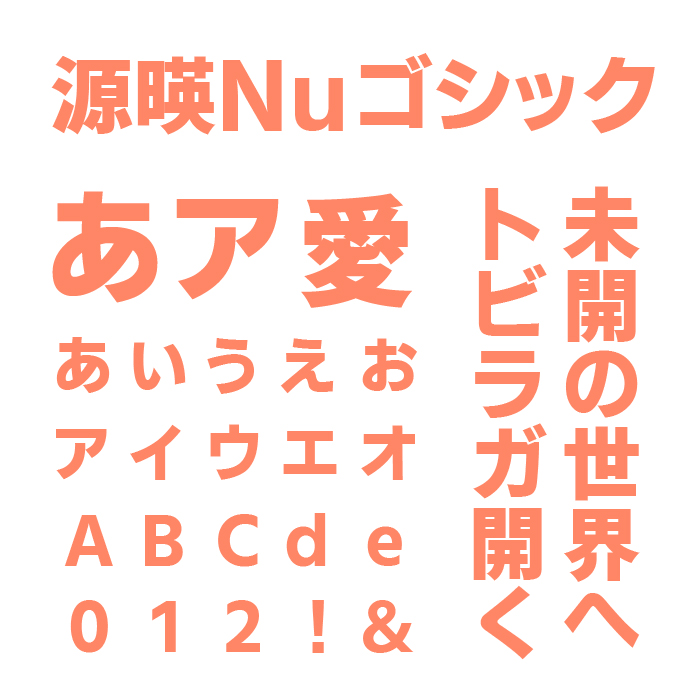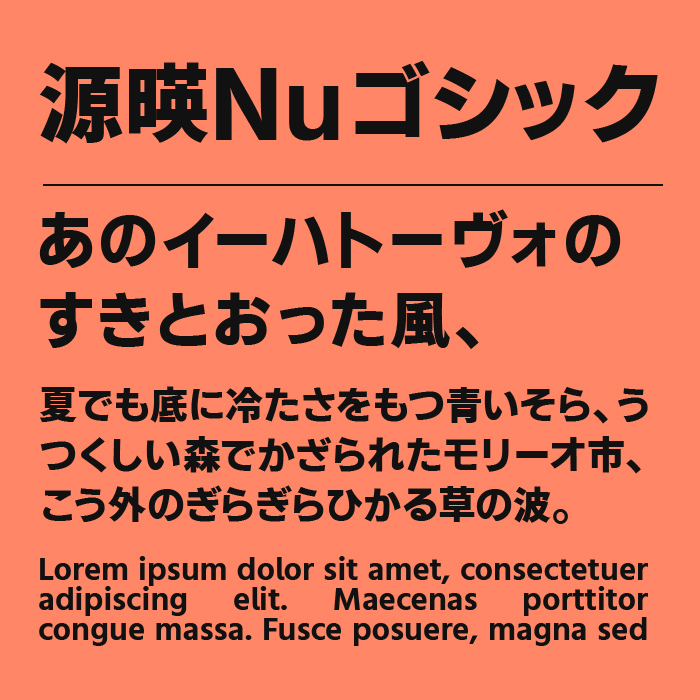
源暎Nuゴシックフォントは、現代的な感性を取り入れた極太ゴシック体で、くっきりとしたウェイトと角の丸みが絶妙なバランスのゴシック体フォントです。
特に太字でも硬さを感じさせず、親しみやすく柔らかな存在感をあるフォントで、マンガの強調セリフ向けとして制作されています。直線的で整然としたフォルムながらも、どこか人の手のぬくもりを感じさせるのが魅力です。
強調セリフ向けとしていますが、ビジネスシーンのプレゼン資料や広告コピー、見出しなどで力強さと読みやすさを両立したい場面などでもぴったりです。多用途に使える万能さがありながらも、Nuならではのわずかなエッジが印象を引き締め、安定感とスタイリッシュさを兼ね備えたフォントです。
収録文字は、漢字・ひらがな・カタカナ・アルファベット・数字・記号が収録。